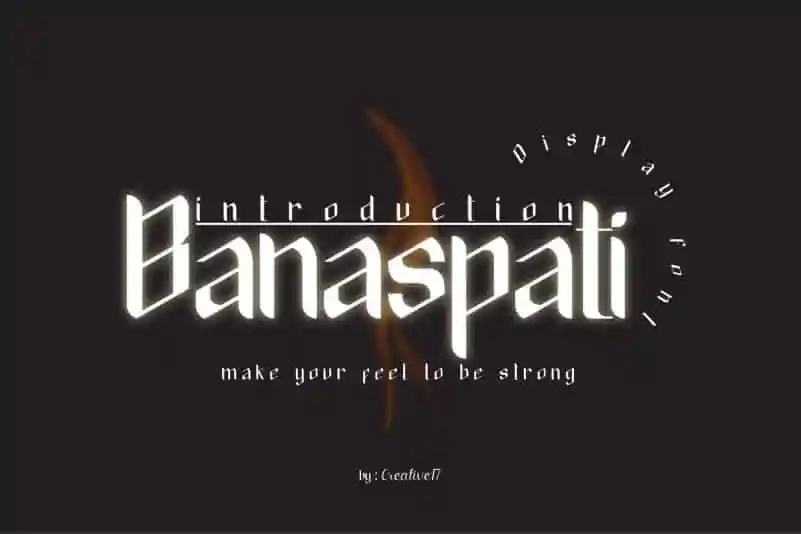
Banaspati Display Font – Download Grátis
Banaspati Display Font é uma escolha versátil para qualquer projeto onde desejas destacar letras com estilo e sofisticação. Ideal para companheiros de logotipos, letras maiores ou menores que fazem parte do título de um filme, você pode usar Banaspati em posters promocionais, revistas, cartazes e muitos outros projetos de design. Irfan Hidayat é o designer responsável pelo desenvolvimento desta fonte que oferece uma combinação única de força, suavidade e limpeza. Composta para trabalhar em qualquer tamanho, seja grande ou pequeno, Banaspati oferece a capacidade de criar designs fortes e elegantes. É perfeita tanto para aplicar na interface do usuário como nas peças de design gráfica. Tente Banaspati agora e veja o poder da sua própria fonte.